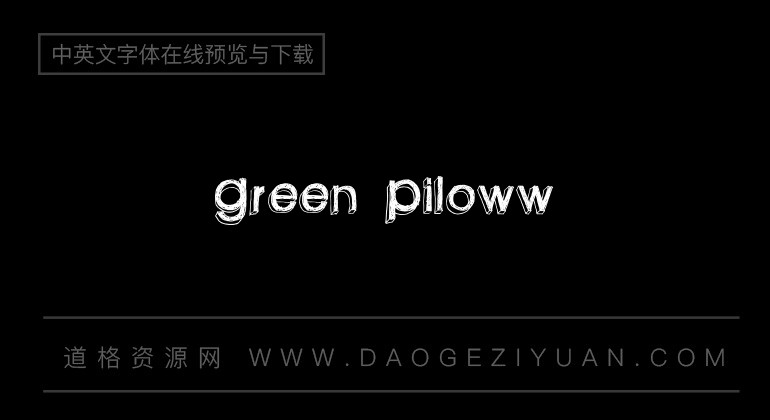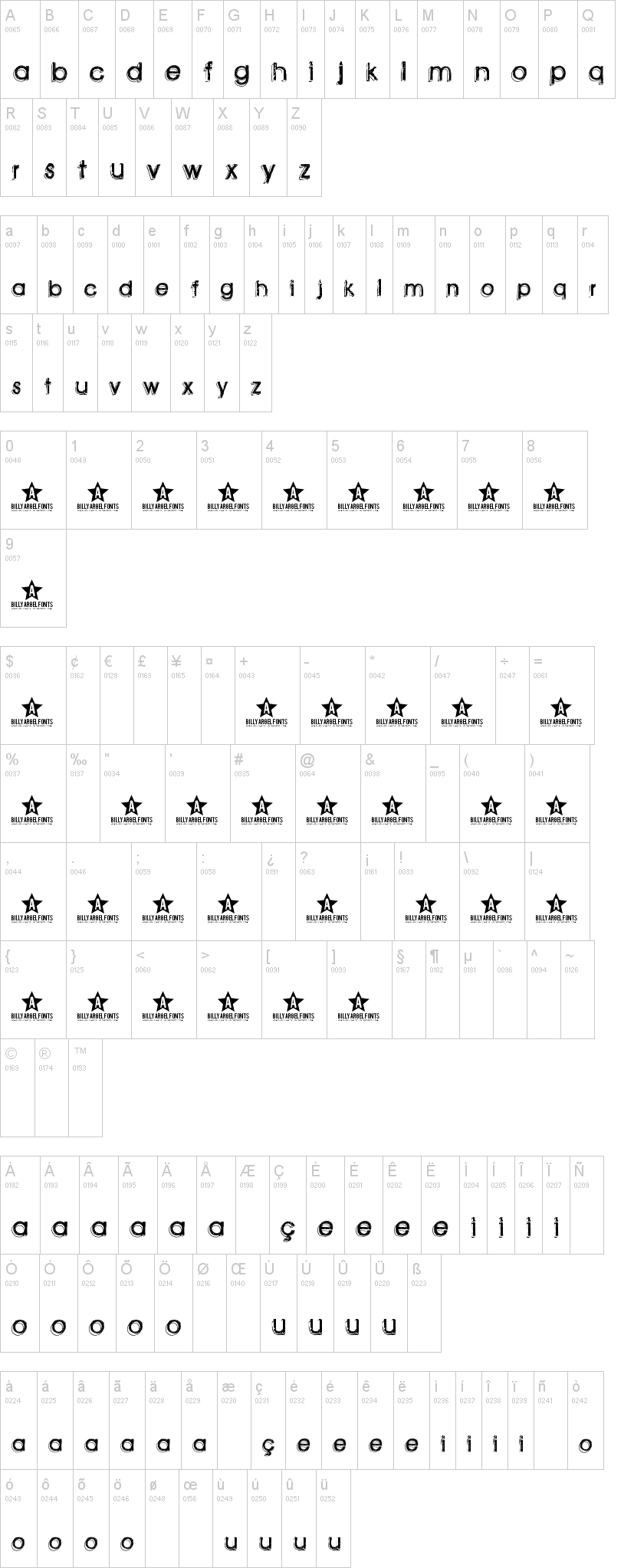
? Green Pilloww 字体是一款拥有古典轮廓的英文字体,它的笔画粗细恰到好处,让字体看起来更加温柔可爱。它的字形比较简洁,但又不失精致,非常适合用来制作海报、招牌或者宣传印刷品等等。内容介绍
Green Piloww是一款非常不错的手写艺术字体,具有很好的视觉感,适合于文化类的宣传设计、商业类品牌的广告和产品包装设计以及个性化文字排版等较多场景。